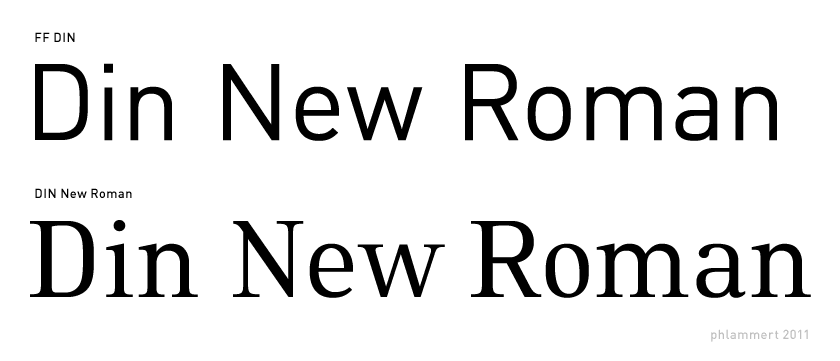
als ich heute im bus darüber nachdachte, ob ich mir die sans-variante der courier von lineto kaufen soll, wunderte ich mich: existiert auch eine (inoffizielle) serif-variante zur ff din? oder gibt es irgendeine schrift, die von der anmutung dem nahekommt, wie man sich eine ff din serif wohl vorstellen müsste?
Muss ja keine Antiqua werden, sondern vielleicht ne SlabSerif.
du nimmst mir die worte aus dem mund, christoph :D eine din-antiqua kann ich mir auch schwer vorstellen.
ich weiss nicht. wenn ich mir das 'a' ansehe ... irgendwie
wirkt mir das alles zu statisch. die din ist nun mal keine
glypha. vielleicht mal mit angeschrägten serifen versuchen.
und was ist mit dem s?
ich weiss nicht. wenn ich mir das 'a' ansehe ... irgendwie wirkt mir das alles zu statisch. die din ist nun mal keine glypha. vielleicht mal mit angeschrägten serifen versuchen. und was ist mit dem s?
nicht falsch verstehen. das ist kein echter »ich zeig euch mal ›meine‹ schrift«-entwurf, sondern nur eine quick&dirty-variante, die ich gerade mal zusammengeschustert habe, damit man sich besser vorstellen, wie ungefähr eine ff din slab aussehen würde. die serifen sind in der tat sehr holzschnittartig, und zu einigen buchstaben (vor allem a, g und s) ist mir auf die schnelle zu wenig oder nichts eingefallen. da es offiziell keine ff din slab gibt und es auch juristisch sicher nicht erlaubt ist, sie für den eigenbedarf zu erstellen, dachte ich eher, dass vielleicht jemand sagt: »ach, die sieht doch aus wie die …!«
jaja, ich habe dich schon verstanden.
aber es überzeugt mich halt nicht wirklich.
auch meine 'quick & dirty' version gefällt mir nicht.
das s wirkt zu breit das a zu schmal. ggf müsste man die ganze schrift
verändern, nur serifen dranschustern ist nicht drin.
ggf müsste man die ganze schrift
verändern, nur serifen dranschustern ist nicht drin.
das ist doch klar, einfach ist das nicht aber es würde bestimmt
erfolg haben, sollte aber lieber albert-jan pool machen,
vielleicht hat er das eh geplant?
ggf müsste man die ganze schrift
verändern, nur serifen dranschustern ist nicht drin.
Nich? Diese Schriftgestalter sind doch die größten Copy&Paste-Benutzer vor dem Herrn! :twisted:
ich bin immer davon ausgegangen das die profis schrift NICHT so
'designen' wie ich als laie :?
Ich dachte mir, ich präsentier euch hier mal dieses kleine Experiment ...
Ich wollte gucken, was passiert, wenn man aus der DIN ein Renaissance-Antiqua macht. Das Ergebnis kommt mir hier etwas hybrid daher. Wahrscheinlich steht den Grundformen der DIN wohl doch eher eine senkrechte Punzen-Achse, wie bei Meta/Meta Serif.
Wer ernsthaft ein Serifen-Äquivalent zur DIN sucht, dem ist wahrscheinlich mit der Droid-Serif geholfen.
Spontan finde ich auch, dass der Strichstärkenwechsel nicht zum Charakter der DIN passt, denn den hat die »normale« DIN ja auch nicht. Ich würde die DIN (nur mal so als Gedankenspielerei) eher mit einer Slab Serif in der Art der Caecilia (in schmaler) ergänzen:
Hmm, das wiederum finde ich nicht passend. :-? Man darf ja bei der DIN den Sinn und Zweck nicht aus den Augen verlieren, für den diese Schrift entworfen wurde. Slabserifen entsprechen viel eher den gradlinigen, klaren und konstruierten Formen der DIN als die Serifen einer Clarendon. Und den Strichstärkenwechsel finde ich bei Deinen beiden Vorschlägen zu dominant, das würde in meinen Augen zu weit wegführen von der DIN. :-)
Das kann ich wirklich gar nicht nachvollziehen — aber so sind die Vorstellungen eben verschieden. ;-)
Es ist doch was ganz normales, daß Schriften ohne (oder mit geringem) Strichstärkenkontrast und solche mit starkem Strichstärkenkontrast gemischt werden.
Du schreibst vom Sinn und Zweck der Schrift, aber der ist doch bei der DIN ein völlig anderer als bei der Caecilia.
Letztere ist schwungvoll, dynamisch, lehnt sich klassischen Antiquaformen und somit auch dem Schreiben mit der Feder an und ist daher stilistisch weit entfernt von der kühlen Konstruktion der DIN.
Die klassizistischen Schriften dagegen, wie auch die ihnen verwandte Clarendon und die Candida, sind konstruiert, geplant, lehnen sich nicht an den dynamischen Duktus der Feder an, und wirken deshalb ähnlich nüchtern und kühl wie die DIN.
Und schließlich wurden und werden solche Schriften genauso wie die DIN für Schilder und andere Beschriftungen verwendet, siehe bspw.:
Hmm, das wiederum finde iUnd den Strichstärkenwechsel finde ich bei Deinen beiden Vorschlägen zu dominant, das würde in meinen Augen zu weit wegführen von der DIN.
So sehe ich das auch.
Sprecht ihr, Kathrin und Joshua, überhaupt über das Gleiche?
Mir scheint es, als läge ein Missverständnis vor.
Naja, es spricht ja nichts dagegen, der DIN eine Renaissance-Antiqua gegenüberzustellen (z.B. Headline, Fließtext). Dazu muss die Antiqua nicht unbedingt genauso konstruiert sein wie die DIN. Sollte eine DIN Serif auf den Markt kommen, würde sie wahrscheinlich wie bei der Meta/Meta Serif eine Schrift sein, mit betonten oder behafteten Serifen und nicht zu starken Strichstärkenunterschieden. Aber es müssen ja nicht alle Antiqua, die einer Grotesk folgen, so aussehen.
Oh, die passt in der Formensprache noch genauer, die kannte ich gar nicht. :gimmifive:
Bei der Copy fehlt mir persönlich aber noch die ein oder andere Serife. Ich würde zum Beispiel dem R eine spendieren und dem w noch ein paar mehr. Aber der Gestalter der DIN Serif, so er denn eines schönen Tages in dieser Sache aktiv werden wird, bastelt der DIN Serif bestimmt ausreichend viele Serifen.